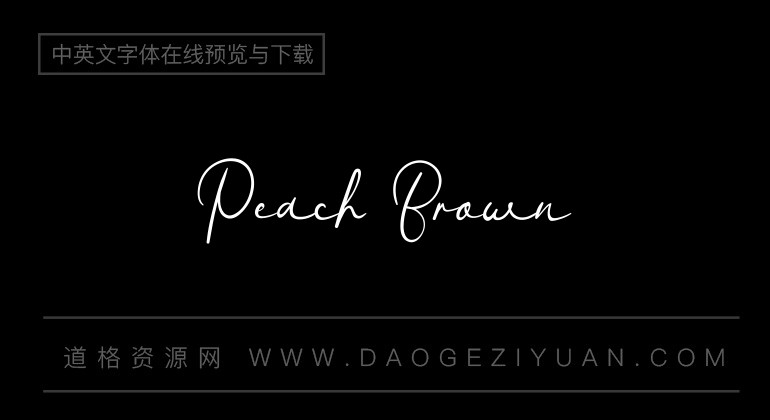
Peach Brown 字体是一种清新、柔和的英文字体,它的字体特征是比较大的字母,这种字体适合用于报纸、杂志和书籍等,它可以增加文字的可读性,使文字更加清晰明了。它的字体设计精致,使用起来舒适,可以让文字更加有趣。内容介绍
Peach Brown是一款非常不错的手写艺术字体,具有很好的视觉感,适合于文化类的宣传设计、商业类品牌的广告和产品包装设计以及个性化文字排版等较多场景。